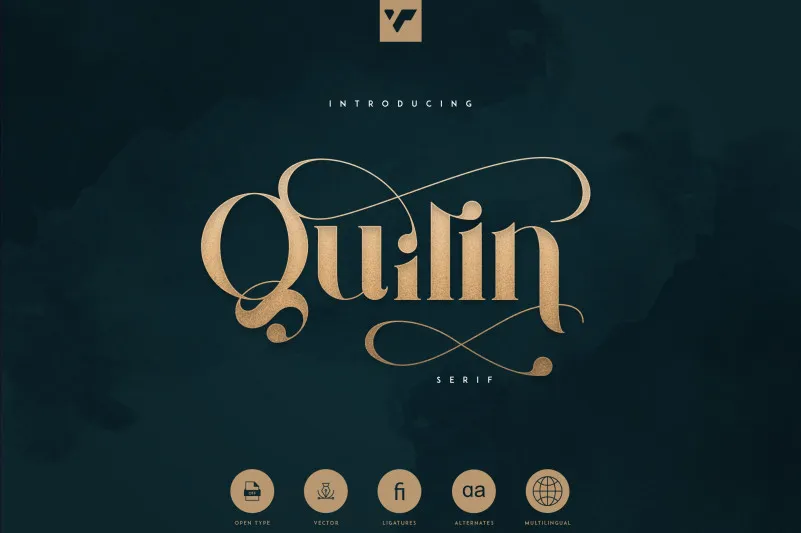
Quilin Serif Font – Download Grátis
A Quilin é uma elegante tipografia serifada que carrega alternativas de letras, ligaduras e suporte multilíngue. Perfeita para trabalhos profissionais de alto padrão, a Quilin oferece uma versatilidade impressionante, adequada tanto em grandes dimensões quanto em textos menores. Suas características distinguem-a como uma opção ideal para designers que valorizam um toque sofisticado e elegante em seus projetos gráficos, seja ela usada no layout de portfólio pessoal ou no design de materiais corporativos. Seja você designer de revistas, publicitário ou editora, a Quilin Seri Serif Font é uma escolha que demonstrará sua preocupação com os detalhes e comprometimento com um trabalho profissionalmente cuidado.